یکی از مهم ترین بخش های هرنوع وب سایتی که باید به آن توجه ویژه ای داشته باشید، بخش فونت یا تایپوگرافی می باشد. فونت مناسب می تواند ساختار یک وب سایت را بهبود ببخشد و یک تجربه جذابی در ذهن خوانندگان ایجاد کند. در هنگام طراحی سایت، تایپوگرافی می تواند نقش بسزایی در ظاهر سایت ایجاد کند، بنابراین نباید ساده از کنار آن بگذرید. هر چند که تعداد فونت های فارسی وردپرس آنقدر زیاد نیست، اما بازهم بسیاری از وب مستران با چالش انتخاب فونت فارسی در وردپرس روبه رو می شوند. به همین منظور ما در این مطلب قصد داریم بهترین فونت وردپرس را که تاکنون ارائه شده است، به شما معرفی کنیم. با ما همراه باشید.
فونت برای وردپرس
اهمیت استفاده از فونت فارسی در وردپرس؟
فونت فارسی وردپرس پایه و اساس یک وب سایت را تشکیل می دهند و می توانند در زیبا و خوانا شدن سایت نقش بسیار مهمی ایفا نمایند. تایپوگرافی کمک می کند تا محتوای صفحات وب سایت شما به صورت خواناتر به مخاطبان نمایش داده شود. نه فقط فونت، بلکه جنبه های مختلف دیگری مانند نوع فونت، اندازه فونت، وزن فونت و… همگی می توانند عملکرد وب سایت شما را گسترش دهند.
اگر شما قصد دارید یک وب سایت طراحی کنید، باید از بهترین فونت برای وردپرس در سایتتان استفاده نمائید، زیرا فونت مناسب می توانند تجربه بهتری در ذهن بازدیدکنندگان سایت ایجاد کند. در واقع؛ بیشتری عنصری که در یک سایت مورد استفاده قرار می گیرد، متن است. بنابراین اگر متنی که شما درج می کنید از ظاهر جذابی پیروی نکند، نمی تواند درک بهتری در ذهن خوانندگان ایجاد کند که همین موضوع باعث می شود که بازدیدکننده خیلی سریع وب سایت شما را ترک کند.
اگر شما صحاب یک وب سایت محتوا محور هستید و قصد دارید مطالب و مقالات مختلفی را در سایتتان منتشر کنید، باید حتماً فونتی را انتخاب کنید که خوانایی مناسبی داشته باشد تا کاربر بتوانند محتوای شما را بدون هیچ گونه مشکلی مطالعه کند. از این رو می توان گفت انتخاب مناسب فونت فارسی در وردپرس، یکی از اصلی ترین بخش های طراحی وب سایت می باشد که از اهمیت ویژه ای برخوردار است.
معرفی بهترین فونت های فارسی وردپرس
همانگونه که انتخاب مناسب فونت های فارسی برای وردپرس می تواند باعث بهبود ظاهر و خوانایی وب سایت شما شود، انتخاب نامناسب و غلط فونت فارسی وردپرس هم می تواند ظاهر سایت شما را بهم بریزد که باعث شود کاربران خیلی سریع وب سایت شما را ترک کنند. بنابراین مهم است که یک فونت مناسب به سایت خود اضافه کنید. با ما همراه باشید تا شما را با بهترین فونت های فارسی وردپرس آشنا کنیم.
1- بهترین فونت وردپرس | ایران یکان
فونت ایران یکان بعد از فونت ایران سنس یکی از محبوب ترین و بهترین فونت های وردپرس می باشد که می تواند برای هرنوع وب سایتی از جمله: سایت فروشگاهی، شرکتی و… مورد استفاده قرار بگیرد. هم اکنون محبوب ترین فروشگاه های اینترنتی ایران مانند: دیجی کالا، شیپور و… از فونت ایران یکان برای بخش تایپوگرافی سایت خود استفاده کرده اند. فونت ایران یکان دارای بیش از 8 وزن می باشد که شما می توانید به دلخواه از آنها استفاده نمائید.
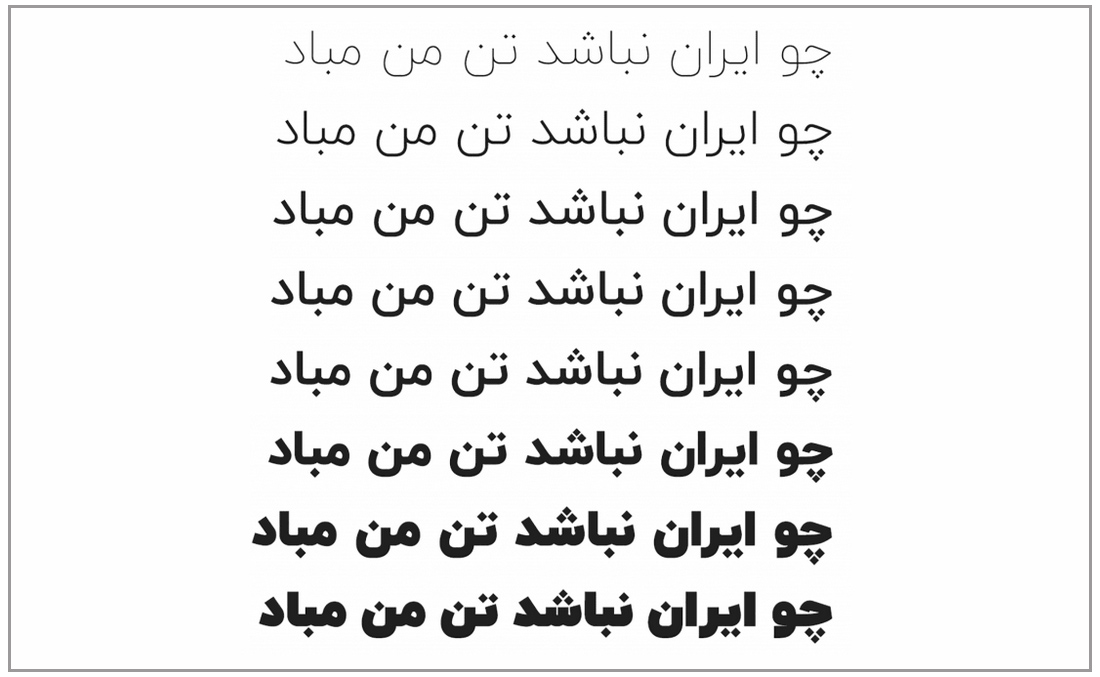
2- بهترین فونت برای وردپرس | ایران سنس
بی شک یکی از بهترین و پرطرفدارترین فونت های فارسی چند دهه اخیر، فونت ایران سنس می باشد. با استفاده از این فونت می توانید ظاهر وب سایت خود را برای کاربران فوق العاده جذاب کنید. در حال حاضر معروف ترین وب سایت های ایران مانند: دیوار، آپارات و… از فونت ایران سنس در سایت خود استفاده کرده اند. این فونت به صورت رایگان ارائه نمی شود و اگر شما می خواهید از آن استفاده کنید باید نسخه قانونی آن را خریداری و سپس آن را به سایت خود اضافه کنید. فونت ایران سنس هم دارای 9 وزن مختلف می باشد که می توانید به دلخواه از آنها در قسمت های مختلف سایت استفاده کنید.
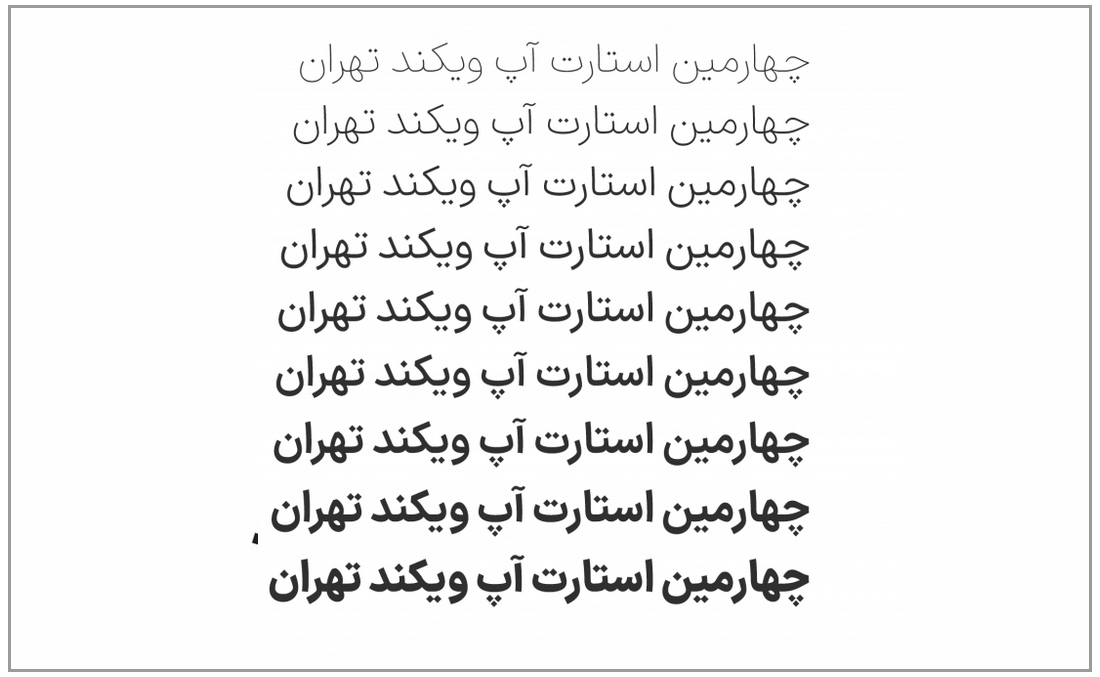
3- فونت فارسی در وردپرس | وزیر
فونت وزیر هم یکی از بهترین فونت فارسی برای وردپرس می باشد که تاکنون ارائه شده است. این فونت دارای ظاهری بسیار جذاب می باشد که می تواند باعث بهبود خوانایی محتوای شما شود. این فونت را می توانید برای هرنوع وب سایتی و هر صفحه ای استفاده کنید. فونت وزیر به صورت کاملاً رایگان ارائه شده است و شما قادر هستید بعد از دانلود آن، چندین وزن این فونت را در اختیار داشته باشید.
4- بهترین فونت های فارسی وردپرس | شبنم
فونت شبنم را هم می توان یک فونت فارسی وردپرس بسیار جذاب دانست. این فونت بر اساس فونت وزیر طراحی و توسعه داده شده است که می توانید از آن برای هرنوع وب سایتی استفاده کنید. این فونت دارای طراحی ساده ای می باشده در میان طرفداران خود از محبوبیت بسیار بالایی برخوردار می باشد. یکی از مزیت های این فونت، رایگان بودن آن می باشد و شما می توانید خیلی ساده آن را دانلود و برای وب سایت خود از آن استفاده نمائید.
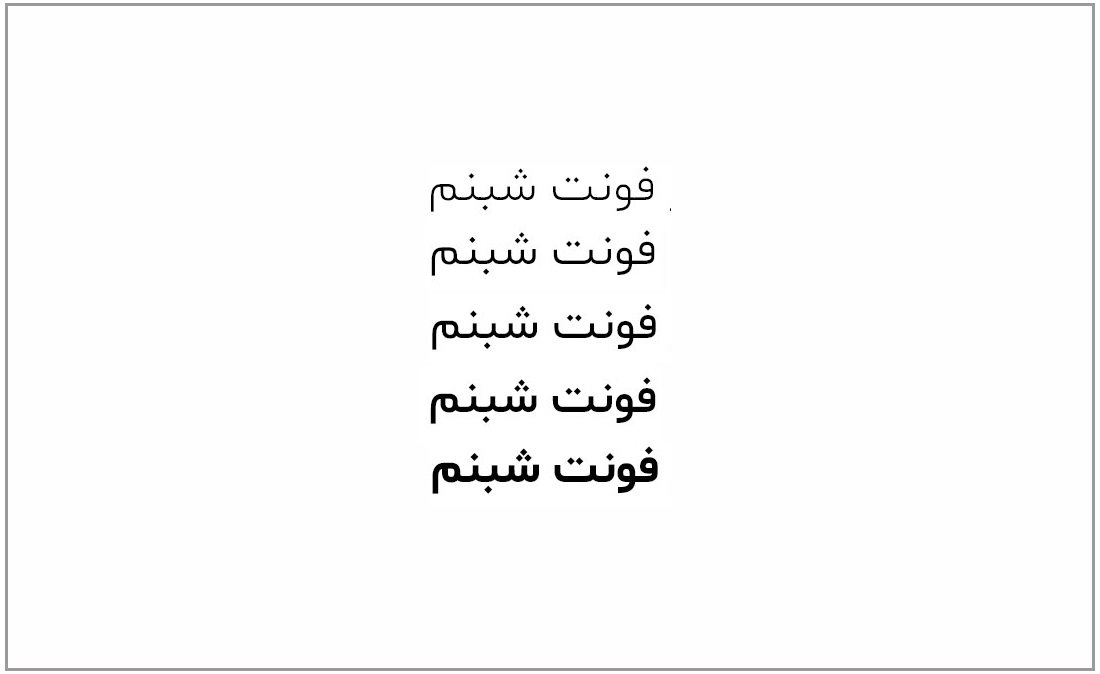
5- بهترین فونت وردپرس | فونت دانا
یکی دیگر از بهترین فونت های فارسی برای وردپرس، فونت دانا می باشد که همراه با بیش از 10 وزن مختلف ارائه می شود. اگر قصد دارید برای سایت خود از فونت یک فونت خاص که کمتر استفاده شده است، بهره مند شوید این فونت می تواند یک انتخاب عالی برای شما باشد. علاوه بر متن محتوا، شما همچنین می توانید از فونت دانا برای طراحی پوسترهای خود استفاده کنید.
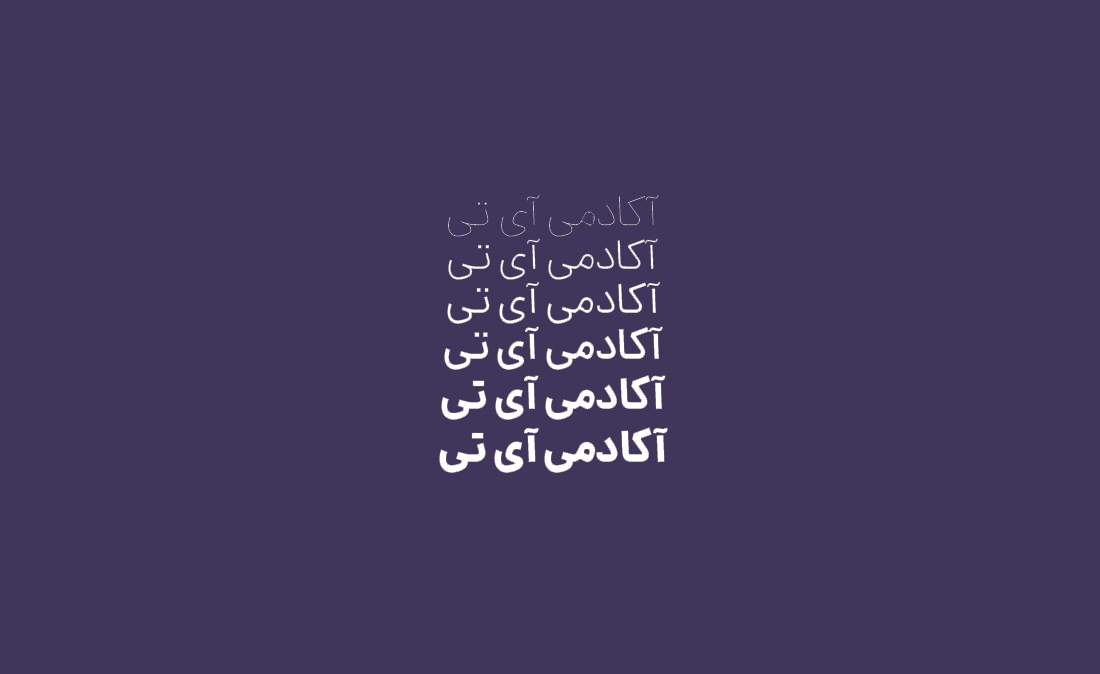
جمع بندی: معرفی بهترین فونت برای سایت وردپرس
متن مناسب می تواند طراحی وب سایت را جذاب کند، بنابراین بسیار مهم است که شما از چه فونتی قصد دارید در وب سایت خود استفاده کنید. ما در این مطلب 5 تا از بهترین فونت های فارسی سایت وردپرس را که محبوب ترین وب سایت های ایرانی از آنها استفاده کرده اند را به شما معرفی کردیم. امیدوارم از این مطلب رضایت داشته باشید.